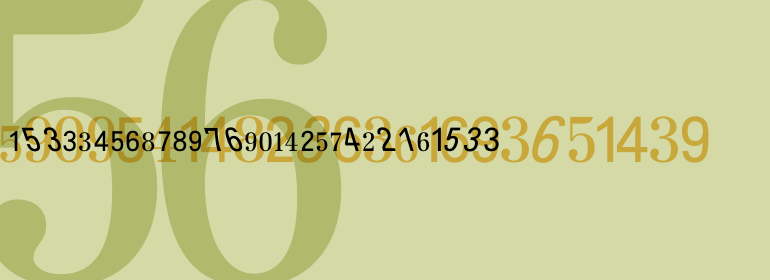
Topografische Zahlentafel™
Topografische Zahlentafel™,这款字体结构工整、笔画清晰,兼顾美观与易读性,适用于标题、正文、海报、包装、LOGO 等多种场景。字形优雅稳定,风格百搭耐看,适配日常排版与创意设计,让文字呈现更舒适、更具质感。Topografische Zahlentafel™一笔一画,皆是细节,以均衡的比例、流畅的线条打造舒适视觉体验,字形端正大气,风格简约现代。无论是商业设计、品牌宣传还是日常排版,都能轻松驾驭,让文字更有格调与力量。Topografische Zahlentafel™字体下载。
字体品牌: Linotype(Monotype) 设计师:Linotype Design Studio 字体分类:衬线体 字体属性:外文 字符集:Unicode 发布时间: 2018